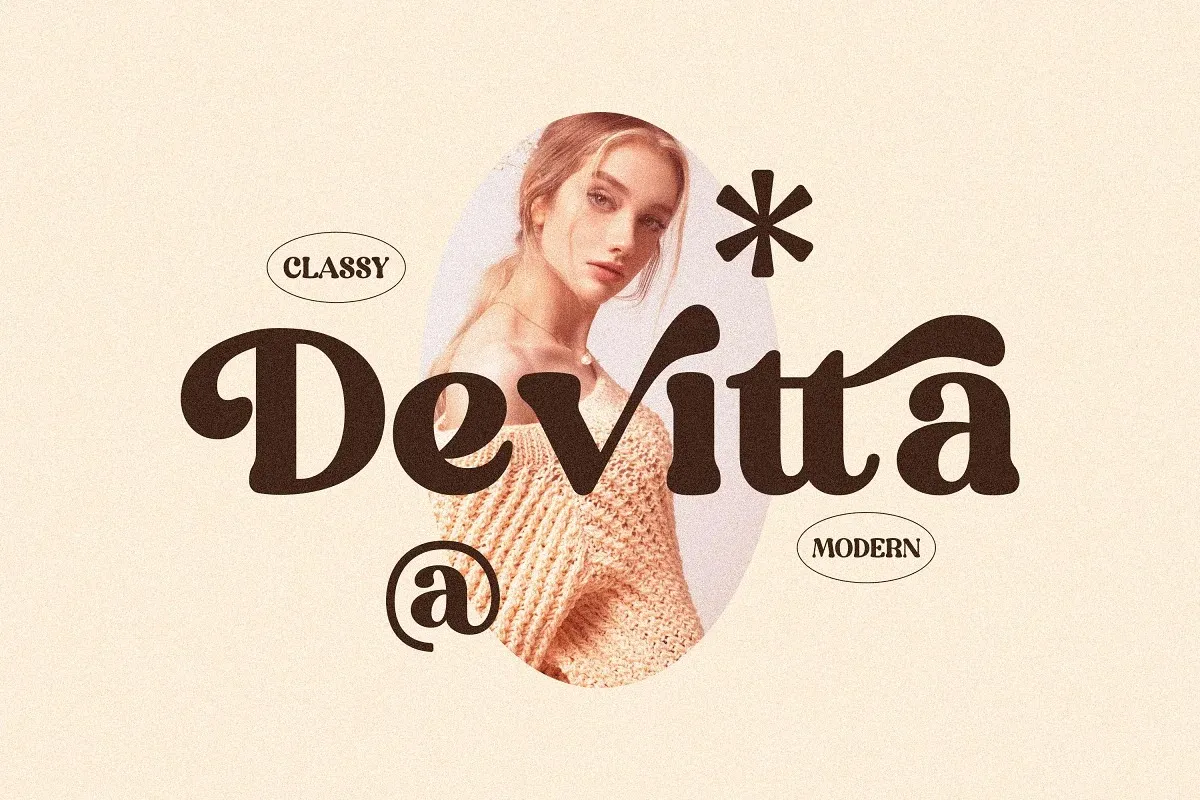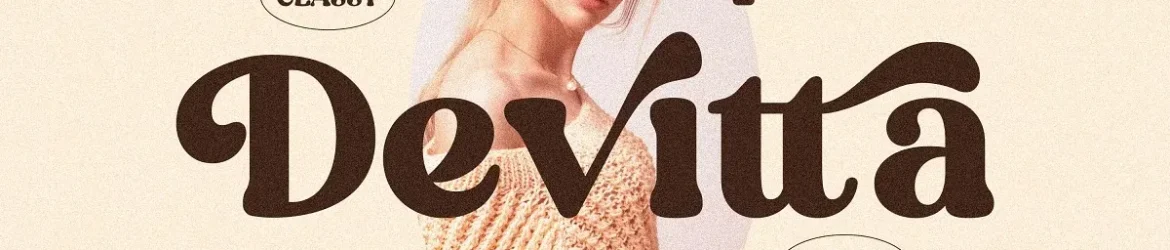
A fonte Devitta é uma elegante serif que traz um ar romântico a cada curva. Criada pelo Storytype Studio, ela é perfeita para estilos modernos de marca, capas de livros ou filmes, marcas de moda, revistas, roupas, assinaturas e citações. Com sua linhas sóbrias e elegantes, Devitta pode dar um toque sofisticado a qualquer design que você realize. Seja para uma capa de livro requintada, o branding de um estiloso marcam de moda ou até mesmo para um projeto gráfico de letras decorativas, essa fonte tem tudo para tornar seu trabalho ainda mais impactante e sofisticado. Experimente adicionar Devitta ao seu próximo design e veja como ela pode transformá-lo em algo único e envolventemente elegante.